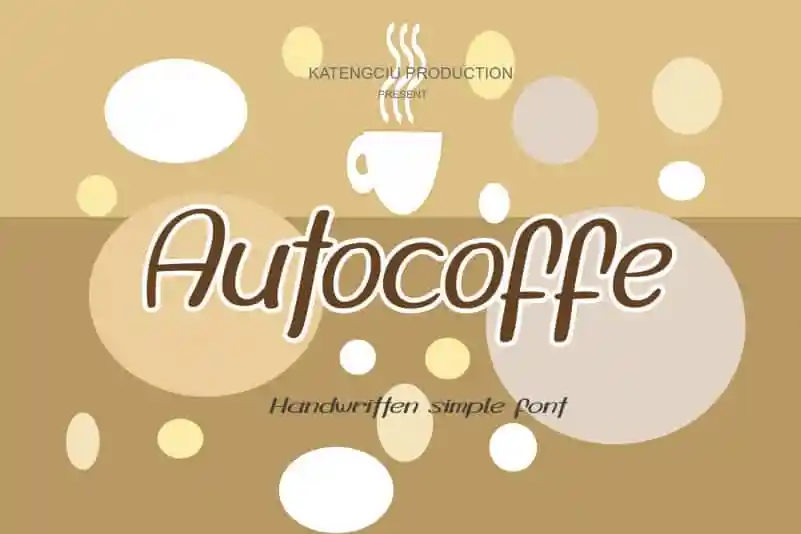
Autocoffe Display Font – Download Grátis
A Autocoffe Display Font é uma elegante fuente escrita a mão que combina simplicidade com adaptabilidade. Suas letras são belas e bem equilibradas, tornando-a perfeita para um amplo range de projetos. Seu estilo versátil certamente o deixará encantado e pronto para criar designs surpreendentes! Esta fuente foi desenvolvida pelo designer Kateengciu, ideal para quem busca uma opção moderna e elegante para suas próximas criações visuais.